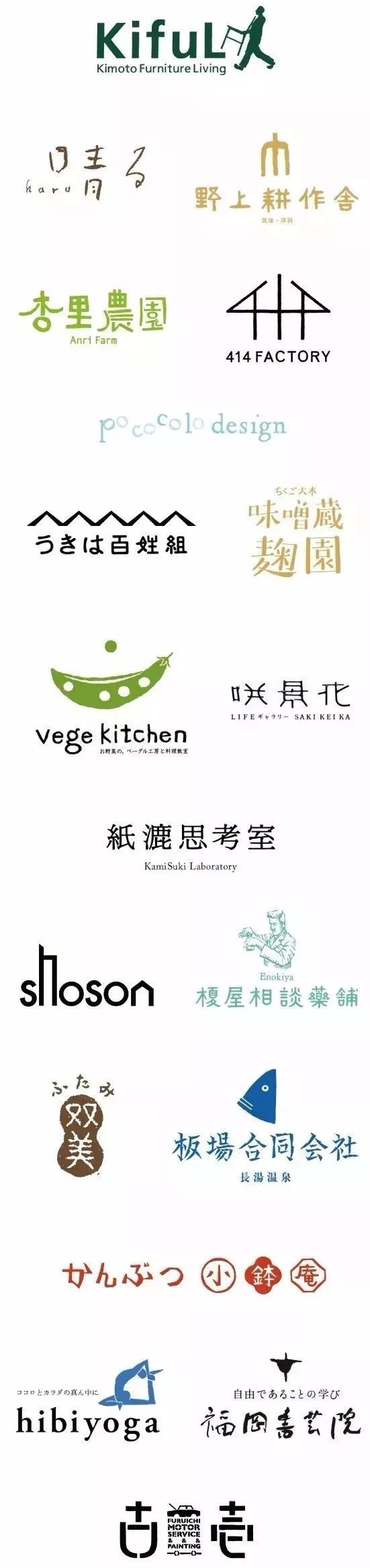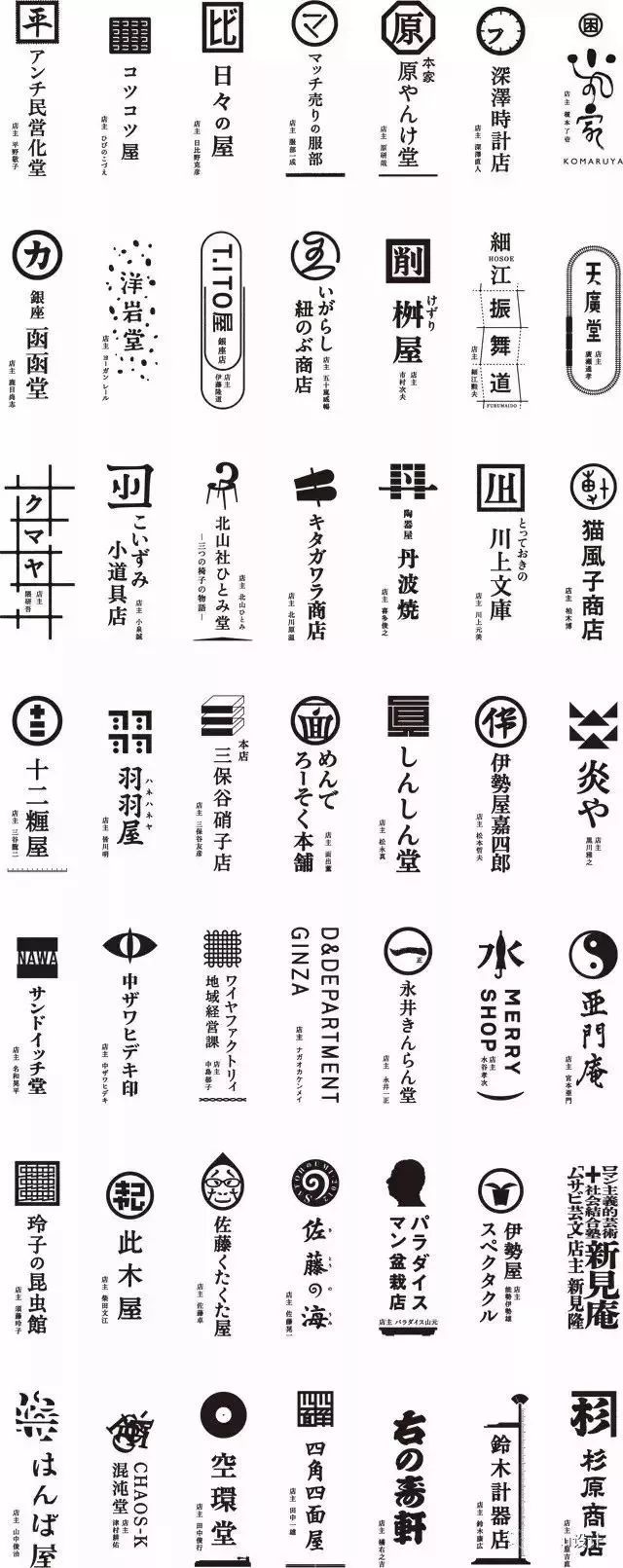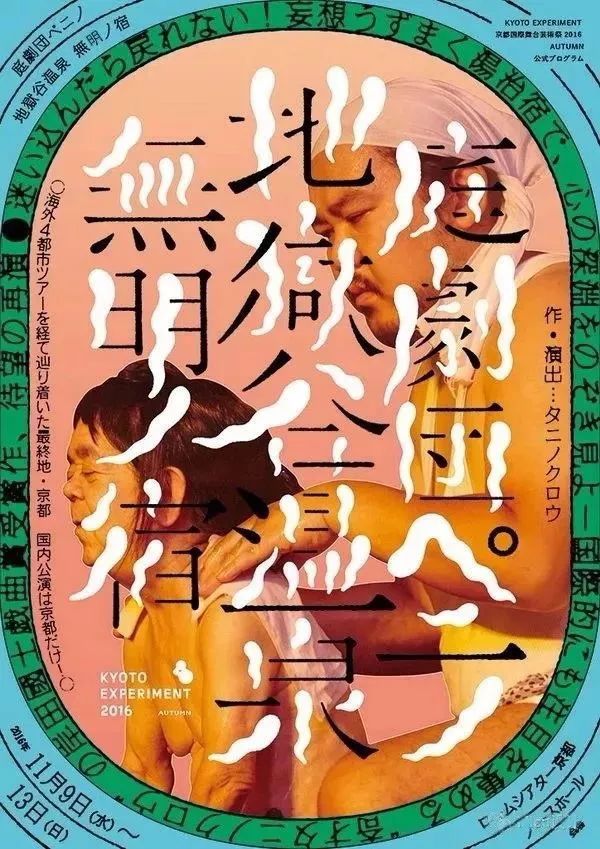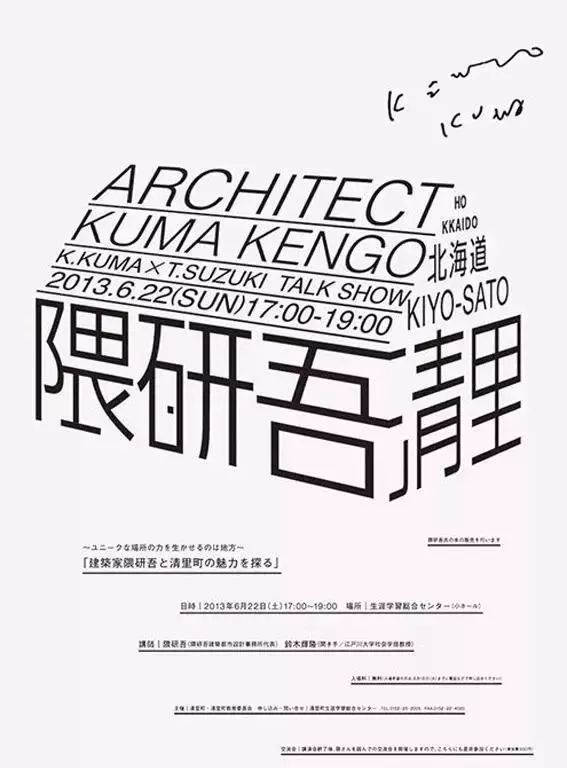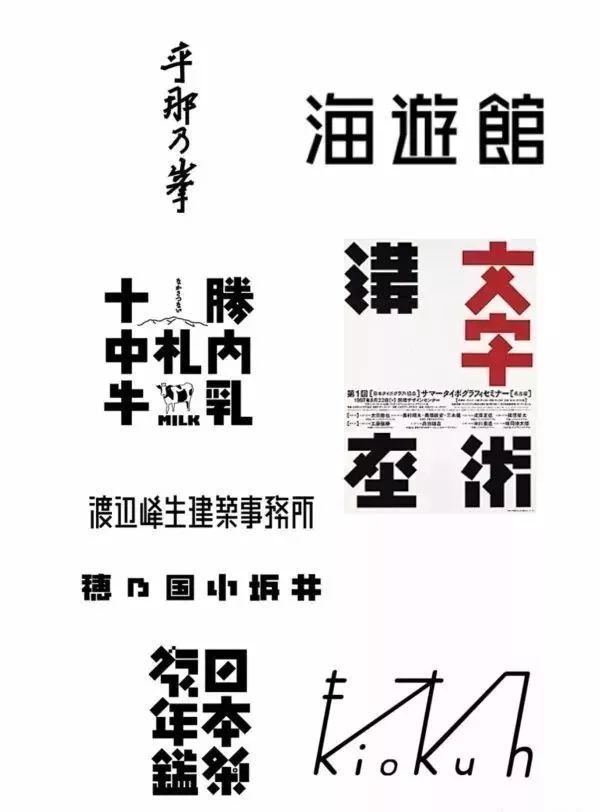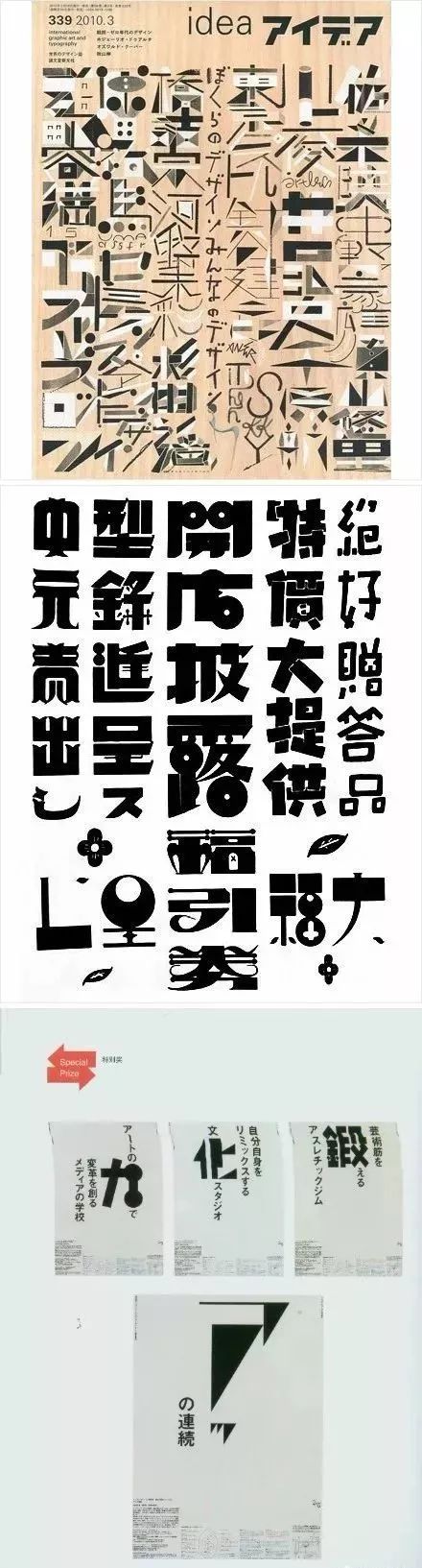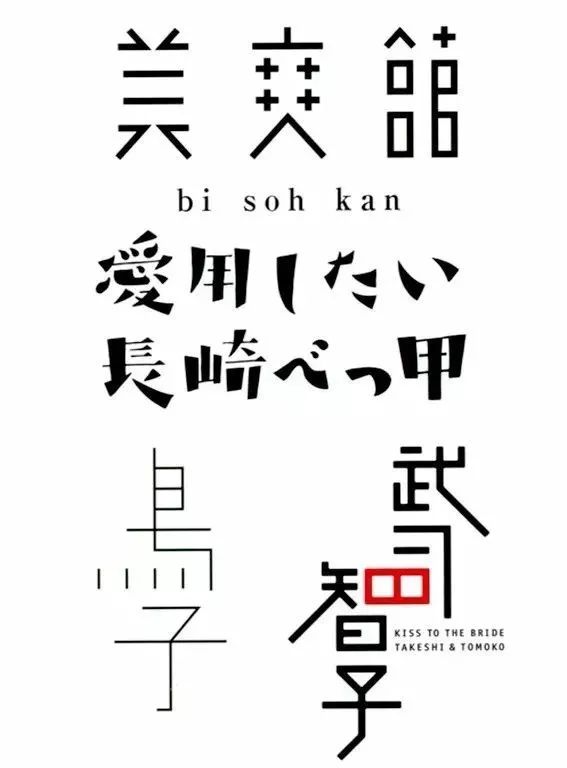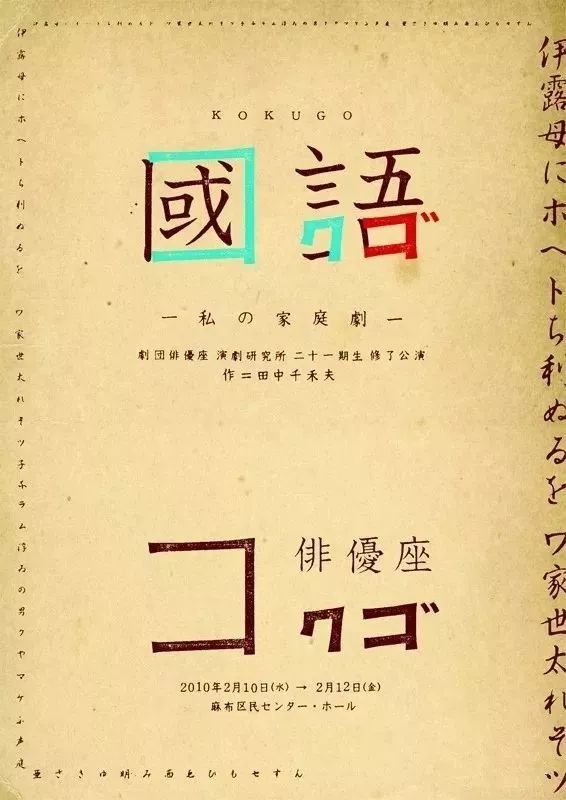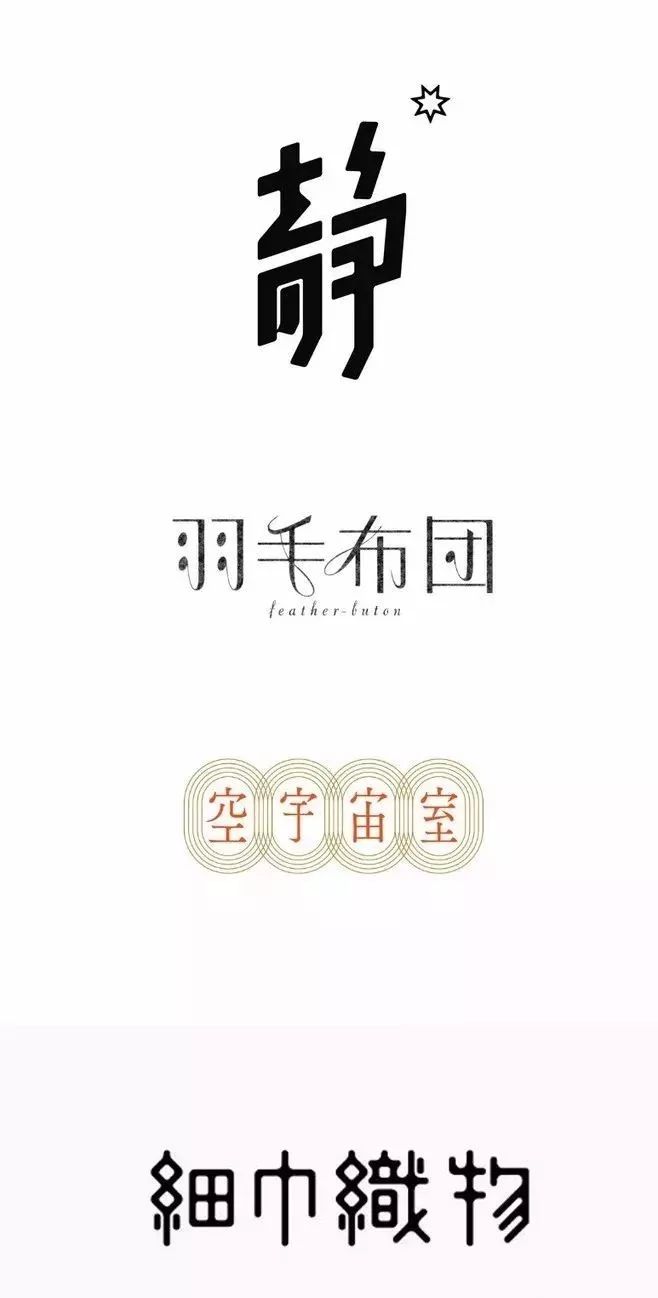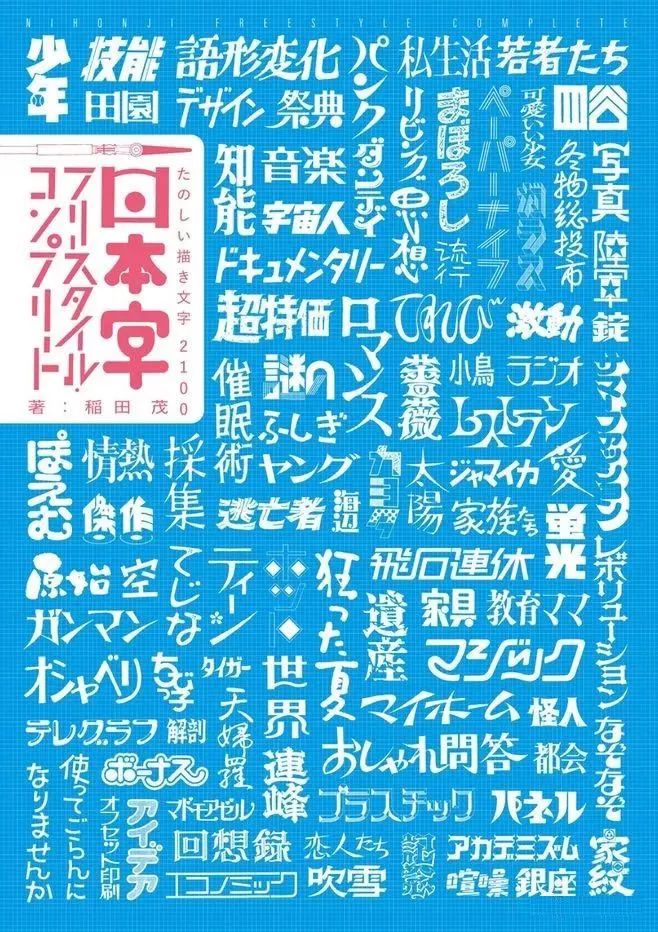
100种日本字体设计分享,值得字体设计师收藏!
好的字体设计,
不仅能传递良好的信息,
并且让人印象深刻。
日本的字体设计
希望大家能够从中借鉴一些设计经验。
从设计作品中,
我们能够看出很强的美感,
不仅对汉字进行了重新设计,
并且结合了所要传达的信息。
每一张作品都具有不同的风格,
设计手法也是花样繁多,
可以说视觉效果非常抢眼……